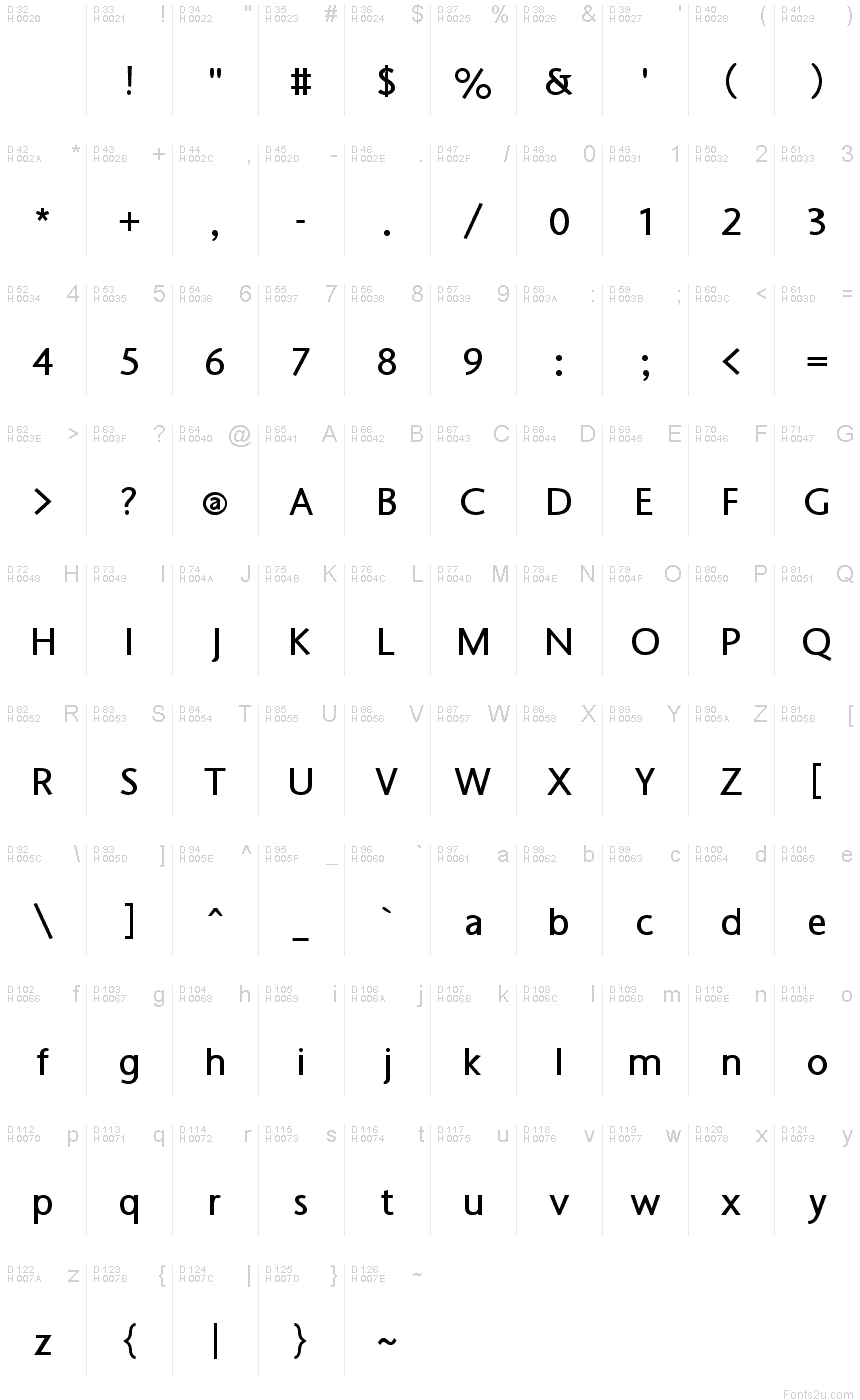
Aboriginal Sans od Chrise Harveyho je bezplatné bezpatkové písmo s přímočarým, současným nádechem. Písmena využívají jednoduché oblé tvary a rovné, vyrovnané tahy, takže celkový dojem je čistý a nekomplikovaný, přičemž široké oblouky a úhledná tečka dodávají písmu jemnou přátelskost.
Přirozeně zapadne do brandingu, redakčních nadpisů, grafiky aplikací, obalového designu i nápisů, kde potřebujete moderní lettering, který působí klidně a přímo. Jako bezplatný font se skvěle hodí i na obálky, titulky a krátké citáty, protože díky kruhovým tvarům a čistým detailům působí i krátká slova stabilně a přístupně.